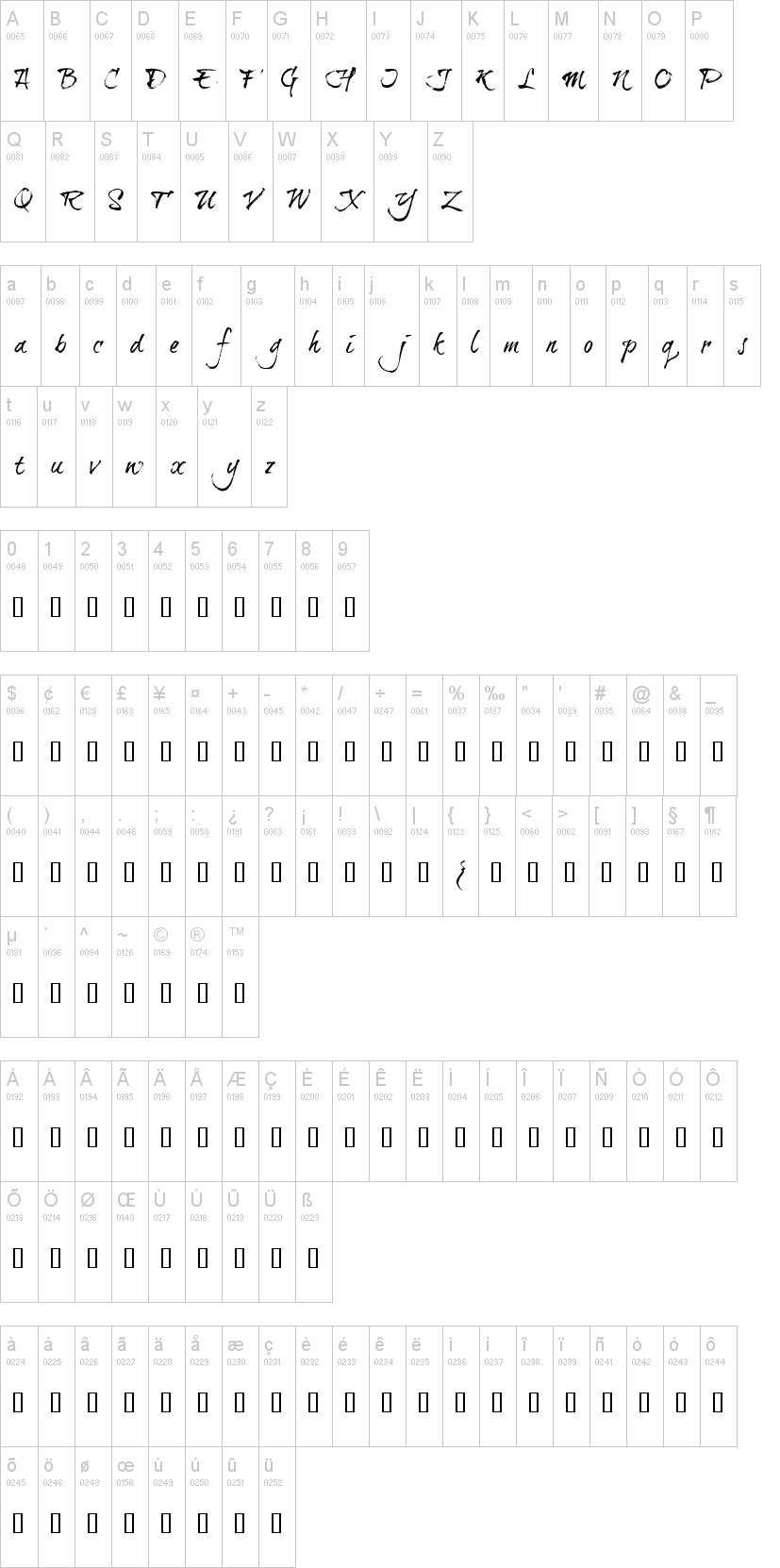
Brushtip Travis 字体是一种手写风格的艺术字体,由设计师 Travis Beckham 创作。这款字体的特点是粗犷、自由、有力,仿佛是用毛笔或刷子书写而成。Brushtip Travis 字体包括大写字母、小写字母、数字和标点符号,非常适合用于标语、海报、书籍封面、广告等设计项目。此外,该字体还支持多种语言,包括英语、德语、西班牙语、法语、意大利语等。Brushtip Travis 字体可以在许多设计软件中使用,如 Adobe Photoshop、Illustrator、InDesign 等。内容介绍
Brushtip Travis是一款非常不错的手写艺术字体,具有很好的视觉感,适合于文化类的宣传设计、商业类品牌的广告和产品包装设计以及个性化文字排版等较多场景。